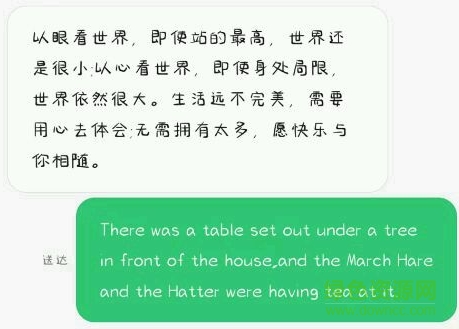
最右體是方正字跡推出的一款個(gè)性鮮明的手寫字體,字跡清新明朗,有著極佳的辨識度和視覺體驗(yàn),歡迎需要的朋友在綠色資源網(wǎng)搶先體驗(yàn)!
方正筆跡最右體,最早出現(xiàn)在小米手機(jī)字體上,受到很多網(wǎng)友的喜歡,字跡柔和有格調(diào),鮮明有藝術(shù)美感,可以廣泛運(yùn)用于海報(bào)設(shè)計(jì)、名片設(shè)計(jì)、藝術(shù)設(shè)計(jì)等多種行業(yè)領(lǐng)域!